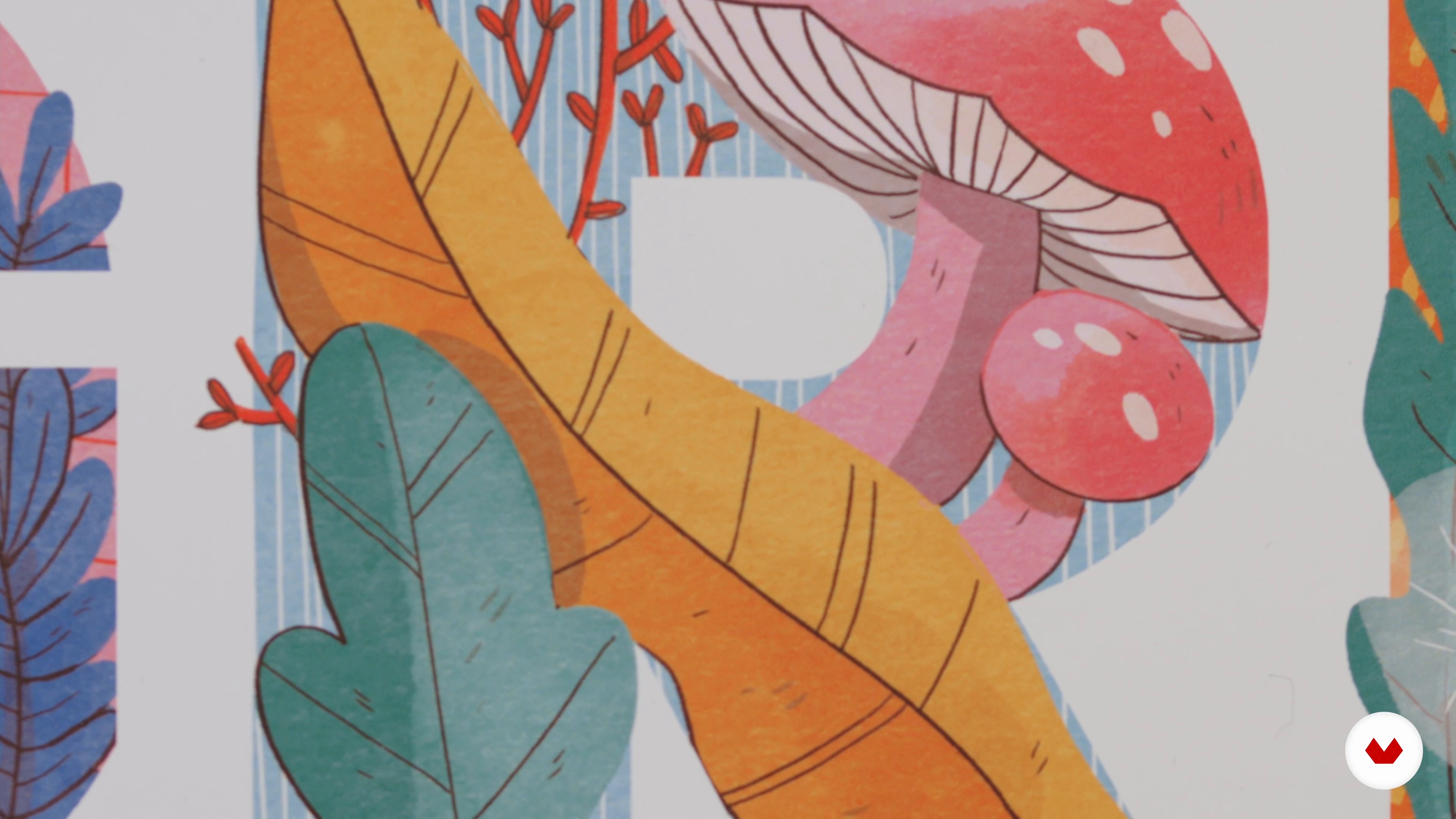
Illustrationen für Kinder: Gestalte eine dekorative Typografie
Fangen wir an
Über die Videolektion: Fangen wir an
“Hier erkläre ich dir, was wir im Kurs machen werden und was du für dein Projekt benötigst. Danach gebe ich dir einige Ideen und Möglichkeiten mit an die Hand, wie du deine illustrierten Buchstaben angehen kannst.”
In dieser Videolektion behandelt Julia Christians das Thema: Fangen wir an, das Teil dieses Domestika-Onlinekurses ist: Illustrationen für Kinder: Gestalte eine dekorative Typografie. Lerne, wie du Typografie und Illustration kombinierst, um mithilfe von analogen und digitalen Techniken eine verspielte Komposition für Kinder zu gestalten.
“Fangen wir an In diesem Kurs lernst du, wie du Zeichnungen und Buchstaben zu einer Illustration kombinierst mit vielen Anwendungsmöglichkeiten. Ich zeige dir, wie du ein Konzept entwickelst und mit Referenzen arbeitest, um mit diesen einen einzigartigen Look zu erstellen. Dabei lernst du wichtige Regeln, wie du Typografie und Illustration in Balance behältst. Die Herausforderung bei diesem Projekt besteht darin, in der beschränkten Form, die der Buchstabe vorgibt, eine Welt zu kreieren und eine Komposition zu erschaffen. Ich arbeite hauptsächlich im Kinderbuch-Bereich. Was du in diesem Kurs...”
Zusammenfassung des Kurses: Illustrationen für Kinder: Gestalte eine dekorative Typografie